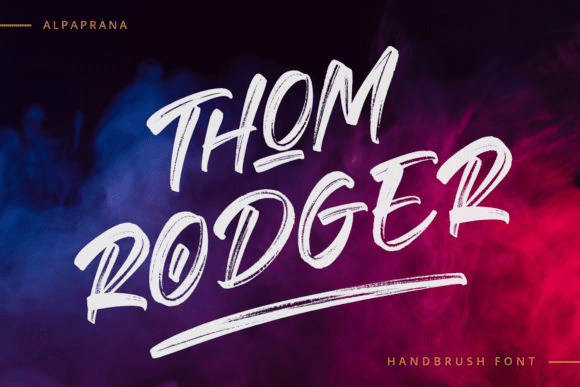
Название: Thom Rodger Font
Том Роджер - это крутой, в городском стиле, шрифт, написанный от руки кистью.
Этот шрифт читается как сильный, уверенный и динамичный и может добавить тонны ностальгического характера вашим дизайнерским работам.